Typografischer Terminus für die Seitenzahl einer Buchseite bzw. Blattseite, ggf. auch für die einer Loseblattsammlung. In der Buchgestaltung wird eine solitär stehende Pagina als »toter Kolumnentitel« oder als »Kolumnenziffer«, eine Pagina mit beigefügten Text, der sich auf den nachfolgenden Seiten ändern kann, als »lebender Kolumnentitel« bezeichnet. Kolumnentitel bzw. Paginas dienen dem Gliedern und dem Ordnen bzw. dem Auffinden einer bestimmten Stelle innerhalb einer Publikation.
Der Stand eines Kolumnentitels bzw. einer Pagina im Faksimile bzw. Layout und die Wahl einer Schriftstilvariante gehören in das Segment der Makrotypografie, der konkrete Schriftschnitt und dessen Zurichtung im Feinsatz in die Mikrotypografie. Bei Schriftmischungen werden tote und lebende Kolumnentitel in einer semantisch-typografischen Auszeichnungsstruktur separat erfaßt.
Etymologisch leitet sich »Pagina« vom lat. »pagina« für »Seite, Blatt, Papier, Kolumne, Schrift, Geschriebenes« ab. Das abgeleitete Verb »paginieren« bedeutet »mit Seitenzahlen versehen«, was im 18. Jahrhundert aus dem lat. »paginare« für »abfassen, schreiben« entlehnt wurde. Lexikalische Abk. »p.« oder »pag.«. In diesem Kontext sind auch die Begrifflichkeiten paginieren, Paginierung, Paginiermaschine oder Paginierstempel zu verstehen.
Die Nummerierung von Handschriften und mittelalterlichen Büchern (z.B. Inkunabeln) wird in der Typografie, in der Paläografie und in der Kodikologie auch als »Foliierung« (Blattnummerierung) bezeichnet. Denn bei Büchern wurden bis zum Ende des 16. Jahrhunderts nicht die Seiten, sondern die Blätter gezählt und mit Blattziffern bzw. Römischen Zählzeichen meist am oberen Rand versehen.
Stand einer Pagina
In der klassischen Buchtypografie befindet sich eine solitär stehende Pagina (toter Kolumnentitel) außerhalb des Satzspiegels eines Buchsatzspiegels, bei Handbüchern (z.B. Taschenbuch) in der Regel im Kopfsteg oder im Fußsteg, bei großen Tischbüchern (z.B. großformatiger Bildband) ggf. auch im Außensteg, sehr selten im Bundsteg. Tote Kolumnentitel können sowohl auf Verso linksbündig und auf Recto rechtsbündig an der äußeren Satzkante ausgerichtet sein, als auch mit Einzügen oder im Axialsatz gesetzt werden. Ähnlich verhält es sich mit lebenden Kolumnentiteln, wobei diese auch im Satzspiegel eines Buchsatzspiegels stehen können.
Verbindliche Vorgaben für den Stand einer Pagina existieren nicht. Paginas werden allerdings von der(n) Kolumne(n) räumlich getrennt, beispielsweise durch eine oder mehrere Leerzeilen. Auch räumliche Trennungen durch Linien oder Zierrat sind üblich.
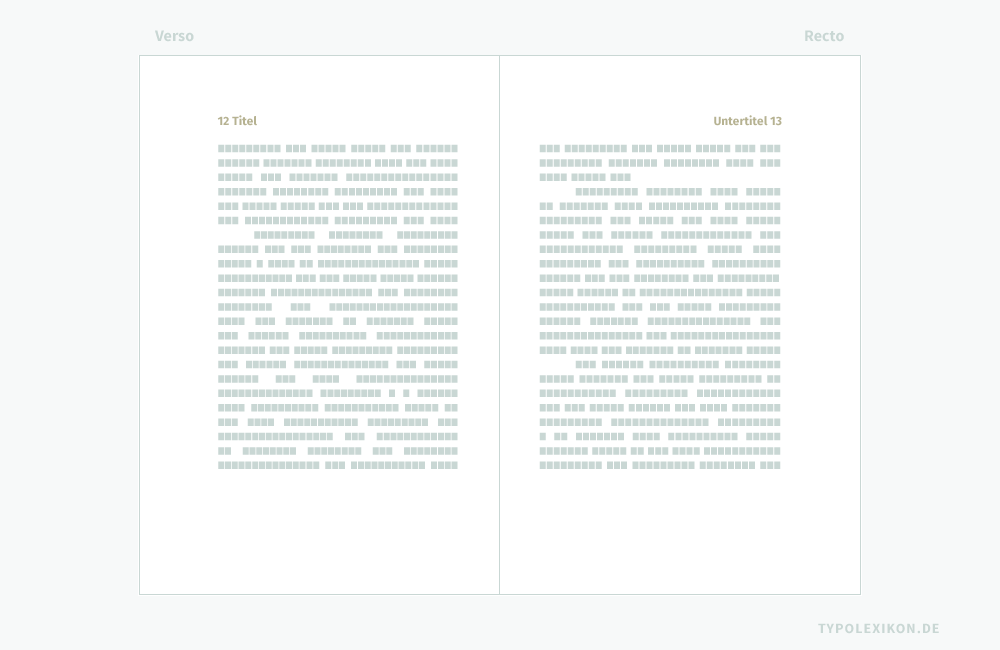
Form und Zurichtung einer Pagina
Verbindliche Vorgaben für den Schriftstil, den Schriftgrad, die Satzausrichtung und die Laufweite eines toten Kolumnentitels bzw. einer Pagina existieren nicht. Bei Romanen genügt eine Seitenzahl aus den Ziffern (vorzugsweise Mediävalziffern) der Werksatzschrift bzw. Textschrift, die normalerweise außen oder in der Mitte im unteren Rand (Fußsteg) der Buchseite steht.
Bei Literatur die selektierendes und konsultierendes Lesen 1) erfordert, beispielsweise Geschäftsberichte, wissenschaftliche Abhandlungen, juristische Texte, komplexe Verzeichnisse oder Schul- und Lehrbücher, ist darauf zu achten, dass die Seitenzahlen beim Umblättern leicht gefunden werden können und dass sie beim Lesen nicht ablenken. 2) Optimal für das Paginieren sind Arabische Ziffern. Römische Zahlen, Buchstaben oder Sonderzeichen sind als Paginas weniger geeignet.
Paginierung eines Buchs
Die Paginierung eines Buches oder einer buchähnlichen Publikation beginnt immer erst nach der Titelei mit dem eigentlichen Inhalt – in der Regel die ersten Anfangsseite (Anfangskolumne) – mit einer ungeraden Seitenzahl (z.B. 5, 7, 9 …) auf einer rechten Buchseite, die als »Recto« oder »Schöndruck« bezeichnet wird. Gerade Paginas (z.B. 10, 12, 14 …) stehen dann auf der linken Buchseite, die »Verso« oder »Widerdruck« genannt wird. Die Seiten einer Titelei werden ab dem Schmutztitel (# 1) zwar rechnerisch mitgezählt, aber nicht paginiert.
Paginierung eines Buches (alphabetisch sortiert):
Bezeichnung | Teilbereich | Pagina |
---|---|---|
Anhang | Abbildungsverzeichnis Abkürzungsverzeichnis Anmerkungen Bemerkungen zu Bildtafeln Bibliografie Danksagungen Dokumentenverzeichnis Glossar Kommentare Literaturempfehlungen Literaturverzeichnis Nachweise Nachwort Ortsverzeichnis Personenverzeichnis Publikationen Quellenverzeichnis Register (Index, Namen- und Sachwortverzeichnis) Sachregister Selbständigkeitserklärung Stichwortverzeichnis Symbolverzeichnis Weiterführende Informationen Zitatverzeichnis | ja |
Anhang | Verlagswerbung | nein |
Buchdeckel hinten | Buchdeckel hinten innen U3 Buchdeckel hinten außen U4 | nein |
Buchdeckel vorne | Buchdeckel vorne außen U1 Buchdeckel vorne innen U2 | nein |
Inhalt | Inhalt ab Anfangsseite, ggf. mit Vorwort ¹ – ¹ je nach Betrachtungsweise | ja |
Schutzumschlag Außenseite | Vorderseite über U1 Klappentext vorne Klappentext hinten Rückseite über U4 | nein |
Schutzumschlag Innenseite | Unbedruckt | nein |
Titelei | Schmutztitel Frontispiz Haupttitel Impressum Dedikation Inhaltsverzeichnis ggf. Vorwort ² – ² je nach Betrachtungsweise | nein |